Guided Course: Erstellen Sie ein Logo mit personalisierter Typografie
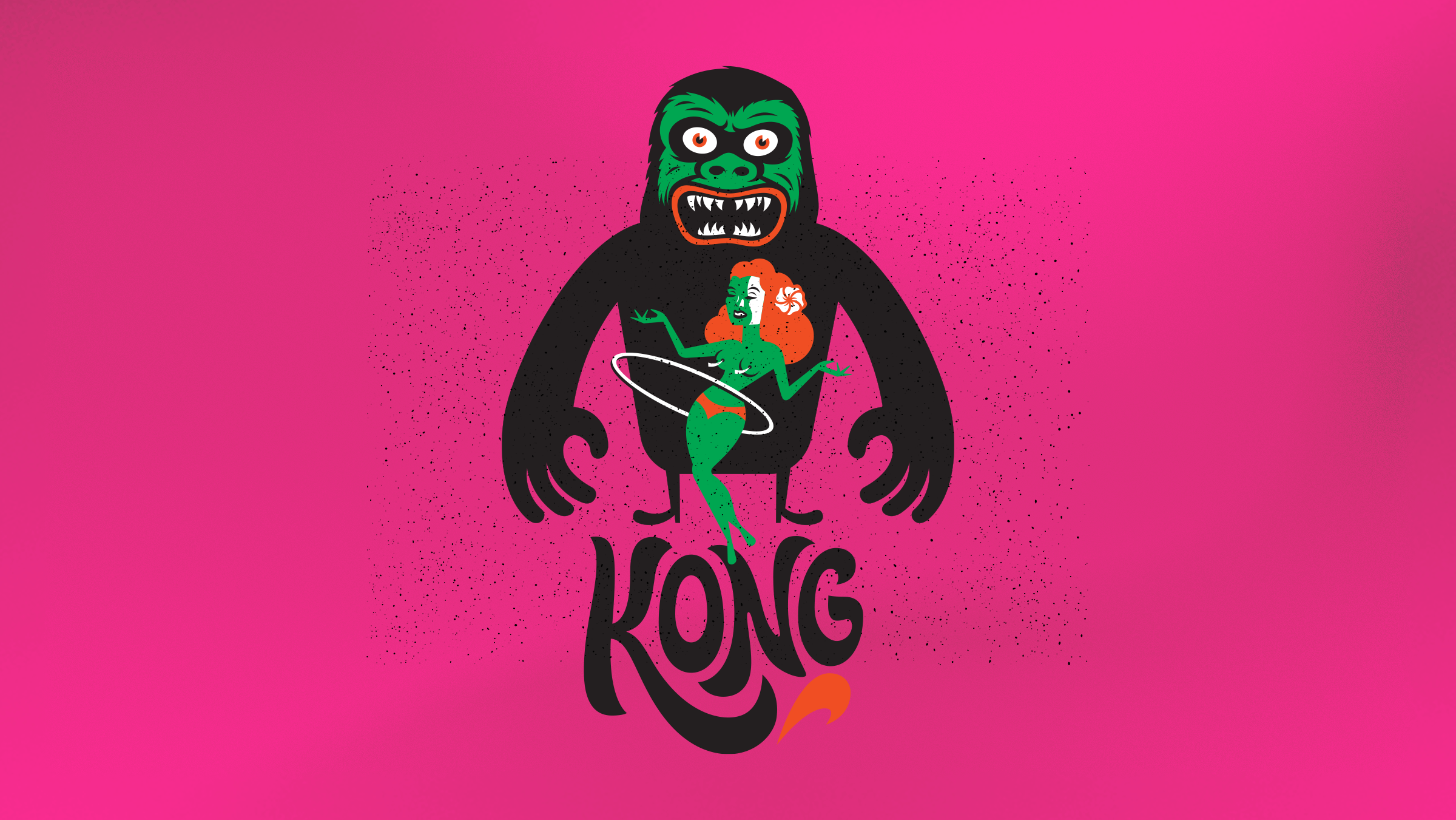
Erstellen Sie einzigartige Logos mit personalisierter Typografie, lernen Sie Skizze, Vektorisierung und Komposition für ein erfolgreiches Branding
Tauchen Sie ein in die faszinierende Welt des typografischen Designs und entdecken Sie, wie Sie einzigartige Logos erstellen, die die Essenz einer fiktiven Marke einfangen. Definieren Sie zunächst das Konzept und sammeln Sie visuelle Referenzen, um ein Moodboard zu erstellen, das Ihre Kreativität anregt. Lernen Sie, Katalogschriften auszuwählen, die zur Identität Ihres Projekts passen, und erkunden Sie Ihre Ideen anhand kurzer Skizzen. Dieser Prozess hilft Ihnen, abstrakte Konzepte in konkrete visuelle Vorschläge umzusetzen.
Digitalisieren Sie Ihre Skizzen, erwerben Sie Kenntnisse in der Vektorisierung und erstellen Sie typografische Elemente mit Adobe Illustrator. Experimentieren Sie mit Komposition und Lock-up und integrieren Sie Text und Bilder harmonisch. Perfektionieren Sie das Design schrittweise und bewerten Sie verschiedene Versionen, bis Sie das Logo gefunden haben, das die Essenz Ihrer Marke am besten repräsentiert. Nach der Fertigstellung verfügen Sie über ein überzeugendes Logo, das die Werte Ihrer Kreation effektiv kommuniziert.
Was ist das Kursprojekt?
Sie entwickeln ein einzigartiges typografisches Logo für eine fiktive Marke. Von der Konzeption bis zum endgültigen Design beschäftigen Sie sich mit der Auswahl der Schriftart, dem Skizzieren, der Vektorisierung und der Komposition und integrieren visuelle und textliche Elemente in ein harmonisches und stimmiges Design.
Grafikdesigner und Kreative, die ihre Fähigkeiten in Typografie und Branding verbessern und mit Vektortechniken individuelle Logos erstellen möchten. Ideal für alle, die den kreativen Prozess vom ersten Konzept bis zur endgültigen Komposition in Adobe Illustrator erkunden möchten.
Quique Ollervides ist ein mexikanischer Grafikdesigner, der sich auf typografisches Design, Branding und Identität spezialisiert hat. Seine professionelle Arbeit umfasst eine breite Palette von Projekten für die Welt der Musik, Unterhaltung, Kultur sowie großer Handelsmarken.
Während seiner Karriere hat er zahlreiche Markenidentitäten, Albumcover und Konzertplakate sowie kommerzielle und persönliche Schriften entworfen.
Zwischen 1996 und 2010 war Quique Mitbegründer des Kreativstudios Hula + Hula, das international für sein meisterhaftes Verständnis von Musik, Humor, Farbgebrauch und Leidenschaft für handgemachte Dinge ausgezeichnet wurde.
Später, zwischen 2006 und 2010, war er Mitbegründer von KONG, einem der wichtigsten Designgeschäfte in Mexiko, das auch als Kunst-, Design- und Illustrationsgalerie fungierte, in der er die Möglichkeit hatte, verschiedene Kunstausstellungen im ganzen Land und zu organisieren und zu kuratieren international.
Quique Ollervides hat auch Typografie- und Designkurse und Kurse an verschiedenen Universitäten unterrichtet und ihre Arbeiten wurden in zahlreichen Büchern, Magazinen und Blogs veröffentlicht.